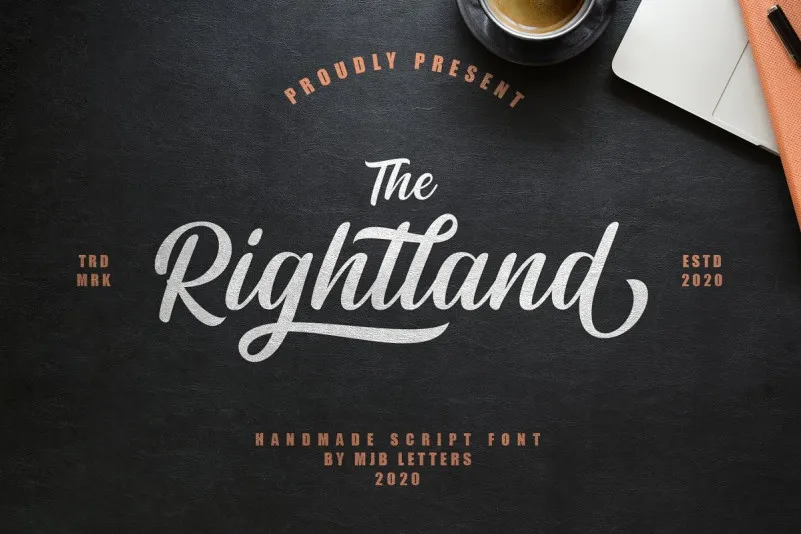
Rightland Bold Script Font – Fonte Grátis
Rightland Bold Script Font
Agora é sua vez de se conectar com uma fonte que vai dar vida a qualquer projeto visual: Rightland Bold Script Font. Esta elegante fórmula script foi criada por MJB Letters e traz um toque natural e forte aos seus caracteres, criados usando canivetes de escrita e traçados meticulosamente até alcançar resultados consistentes. É uma fonte bold script moderna que impressiona pela sua força e clareza, com suas elegantes espigas em cada curva pronta para ser aplicada a vários tipos de necessidades de design como logotipos, posters, embalagens de marca e muito mais. Suportando múltiplas línguas e as características OpenType, esta fonte oferece uma experiência de uso completa graças ao PUA encoded. Seja você um designer gráfico ou criador de arte digital, a Rightland Bold Script Font é o aliado perfeito para seus projetos. Sua simplicidade e versatilidade garantem que ela seja útil em qualquer tipo de projeto visual, desde logotipos resistentes até peças publicitárias impecáveis. Experimente hoje esta fonte poderosa que promete revolucionar a forma como você cria design.